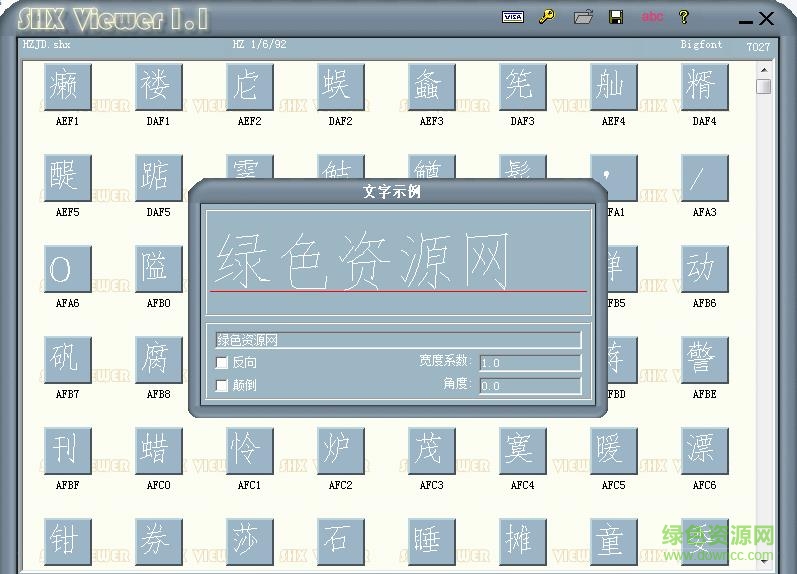
hzjd.shx擁有十分嚴(yán)謹(jǐn)?shù)奈淖謽邮剑屇阍谑褂弥兄谱鬟^程中能夠感受到最佳的顯示效果他,為了讓用戶們能夠打開更多制作圖紙,這款字體也是必不可少的!
現(xiàn)在大多數(shù)設(shè)計單位對圖紙使用的字體都有要求,這樣可以保證內(nèi)部設(shè)計交流或合作時不出現(xiàn)字體方面問題